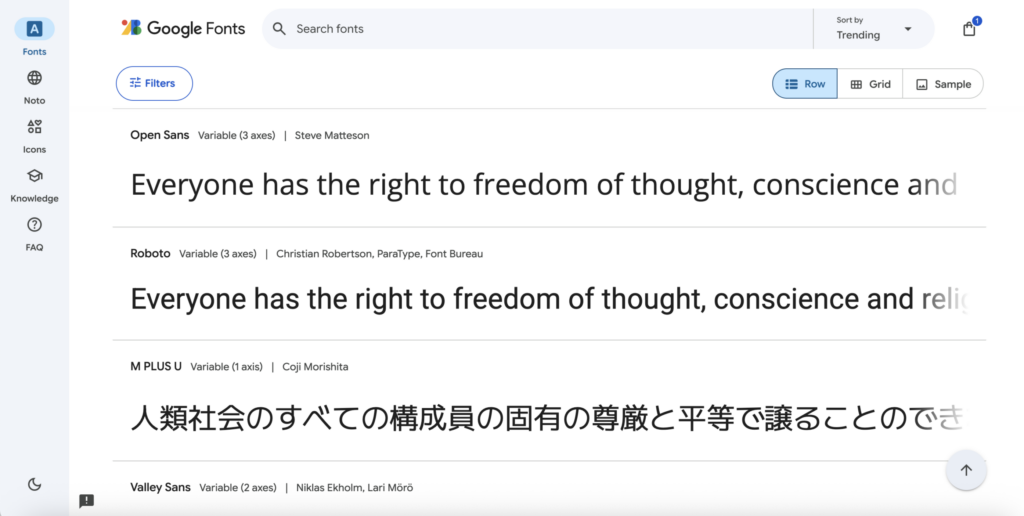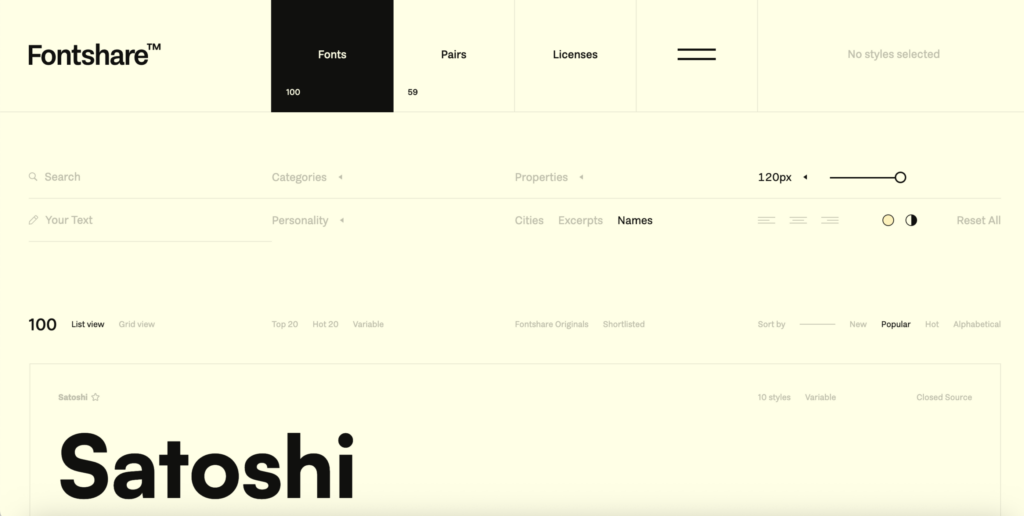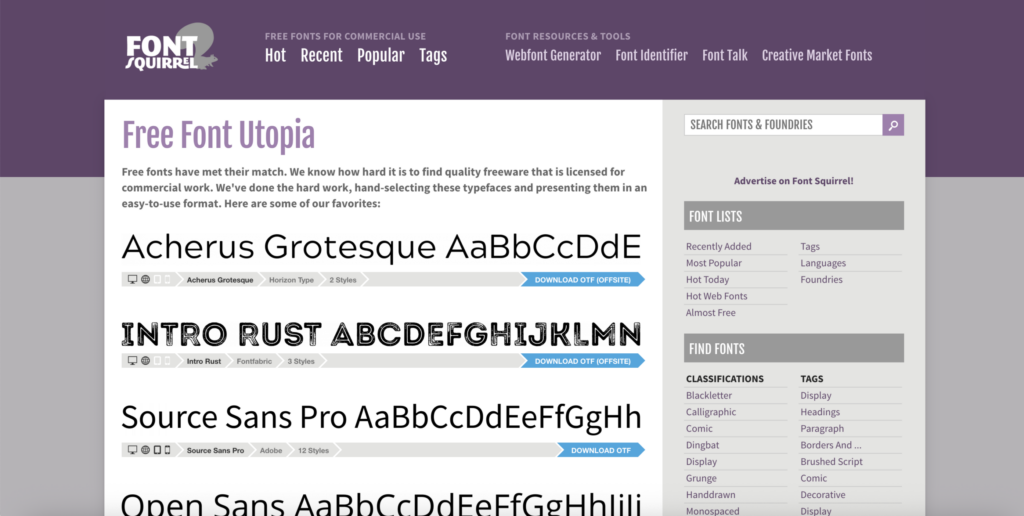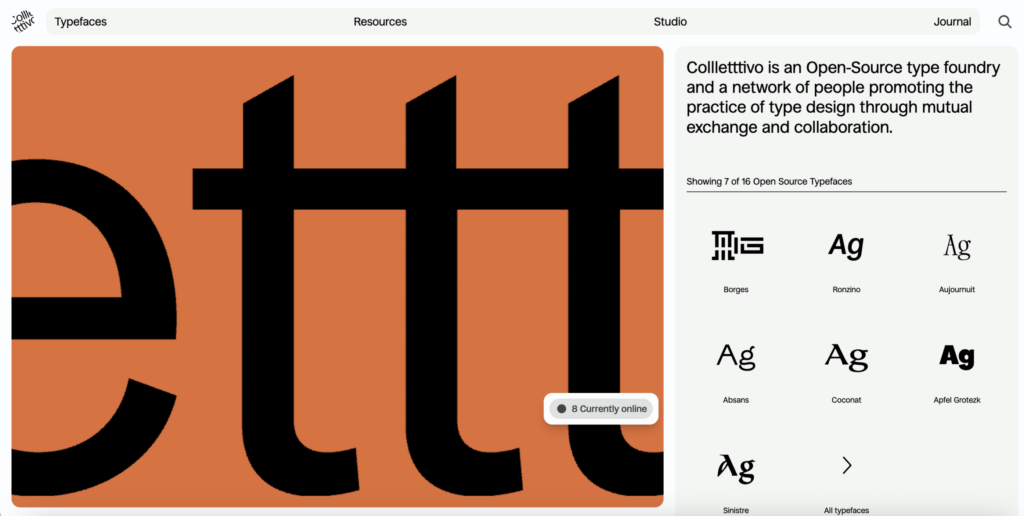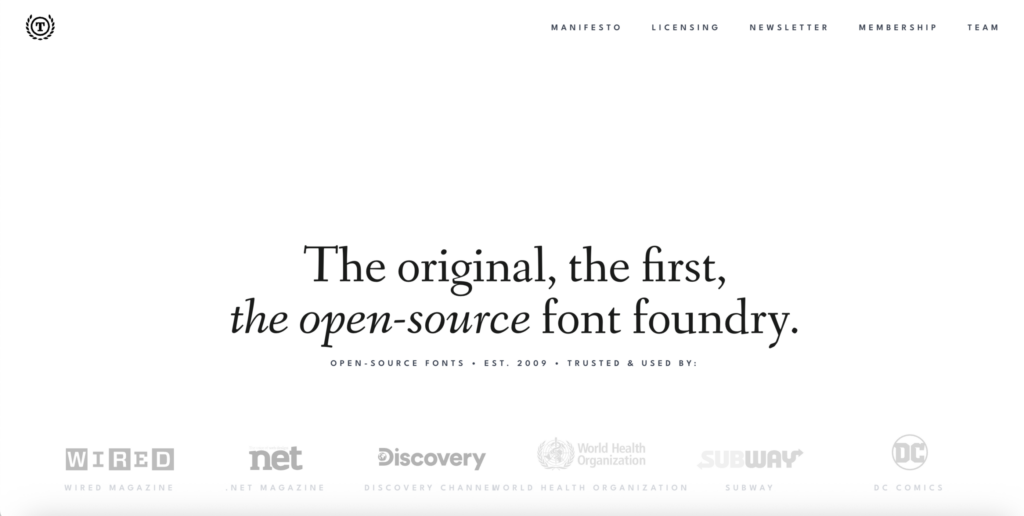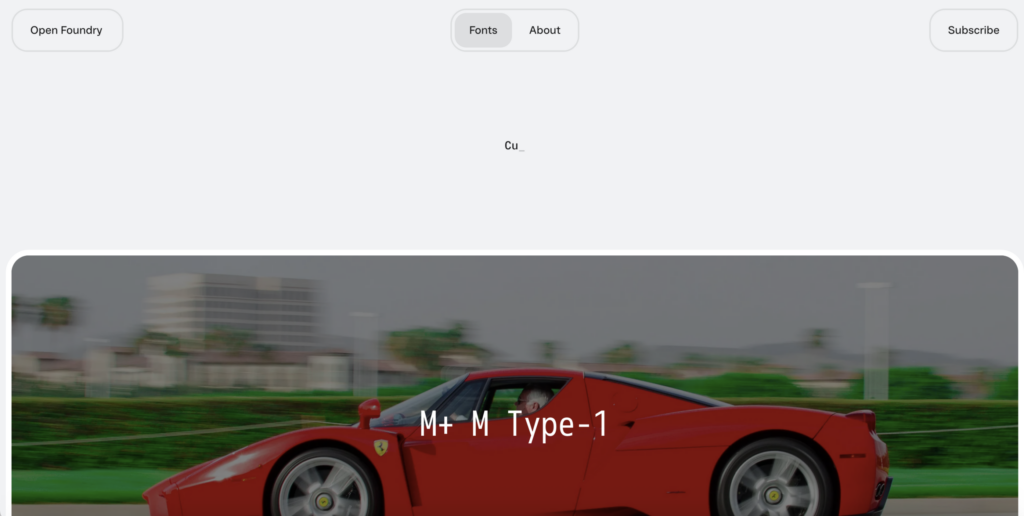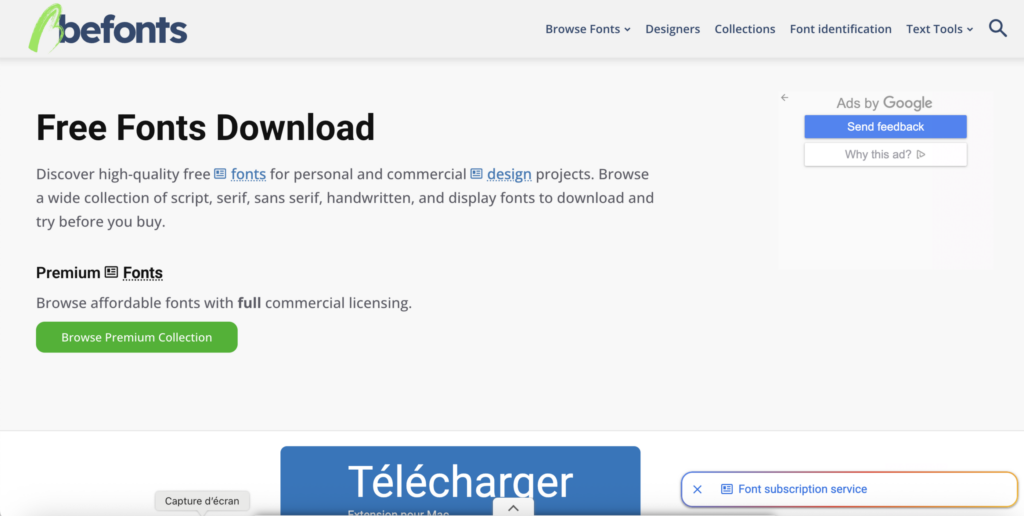
¿Dónde encontrar tipografías bonitas y gratuitas para proyectos comerciales?
Acabas de encontrar la tipografía perfecta. Encaja con tu logotipo, transmite exactamente el tono que buscabas y ya te imaginas utilizándola en todas partes.
Entonces abres la licencia: Solo para uso personal. Y vuelta a empezar…
Porque una tipografía gratuita no es necesariamente gratuita para proyectos comerciales. Utilizar una fuente en el logotipo de un cliente, en un packaging, un cartel, una campaña publicitaria o cualquier soporte destinado a una empresa puede requerir una licencia específica.
Por suerte, hoy en día existen muy buenas plataformas para encontrar tipografías gratuitas, de calidad y utilizables en proyectos profesionales.
Aquí te proponemos unas muy interesantes.
Tipografías gratuitas: ¿se pueden usar en proyectos comerciales?
Antes de descargar una tipografía, hay que tener en cuenta lo siguiente:
Una tipografía puede ser:
• gratuita únicamente para uso personal;
• gratuita para determinados usos comerciales;
• totalmente libre para proyectos personales y comerciales;
• ofrecida bajo una licencia de código abierto;
• disponible gratuitamente en versión de prueba, pero de pago para su uso final.
Y la diferencia es importante.
Crear una invitación de cumpleaños con una tipografía gratuita no tiene las mismas implicaciones que utilizarla en la identidad visual de una empresa o en 10.000 envases.
Por eso, antes de utilizar una tipografía en un proyecto profesional, comprueba siempre la licencia asociada a ella.
1. Google Fonts: una apuesta segura para proyectos comerciales
Google Fonts es probablemente la plataforma más sencilla para encontrar tipografías gratuitas para utilizar en proyectos profesionales.
Las tipografías disponibles se distribuyen bajo licencias de Open Source (código abierto) y pueden utilizarse tanto en proyectos personales como comerciales. Google indica expresamente que pueden utilizarse en proyectos comerciales.
La biblioteca es enorme y contiene todo tipo de tipografías:
• serif;
• sans serif;
• tipografías display;
• monoespaciadas;
• script;
• fuentes variables.
Entre ellas encontramos familias que se han convertido en imprescindibles, como Inter, Poppins, Manrope, DM Sans, Playfair Display o Space Grotesk.
Ideal para: branding, sitios web, publicaciones, carteles y proyectos para clientes.
Lo mejor: las licencias son mucho más fáciles de entender que en las plataformas que combinan distintos tipos de derechos.
2. Fontshare: para encontrar tipografías gratuitas con un acabado realmente premium
Fontshare es probablemente una de las mejores alternativas a Google Fonts cuando buscas algo con más personalidad.
La plataforma fue creada por Indian Type Foundry y ofrece una selección de tipografías de calidad profesional.
Lo más importante es que Fontshare especifica que todas las tipografías de su catálogo son gratuitas para uso personal y comercial. Según la familia tipográfica, se ofrecen bajo una licencia de código abierto o bajo una licencia gratuita propia de Indian Type Foundry.
La diferencia con algunas de las grandes bibliotecas de tiografias gratuitas se aprecia enseguida: la selección se acerca mucho más a lo que esperaríamos de una fundición tipográfica premium.
En ella encontrarás tipografías especialmente adecuadas para:
• identidades visuales;
• titulares editoriales;
• campañas publicitarias;
• sitios web;
• presentaciones de marca.
Ideal para: identidades modernas y proyectos que quieran evitar el efecto de «Google Fonts de siempre».
Lo mejor: una selección de gran calidad y una licencia comercial clara.
3. Font Squirrel: el especialista en tipografías gratuitas para uso comercial
Font Squirrel se ha creado precisamente en torno a esta cuestión.
La plataforma selecciona principalmente tipografías que cuentan con una licencia que permite su uso comercial gratuito.
Aun así, es importante consultar la licencia específica de cada tipografía, ya que algunos usos concretos, como la integración en una aplicación o en un archivo digital, pueden estar sujetos a condiciones diferentes.
Visualmente, el sitio es algo menos actual que Fontshare, pero su catálogo sigue siendo muy interesante.
Además, puedes filtrar las tipografías por:
• serif;
• sans serif;
• script;
• display;
• retro;
• condensadas;
• monoespaciadas.
Ideal para: buscar una tipografía de uso libre para un proyecto de cliente sin tener que revisar cientos de licencias de «solo para uso personal».
Lo mejor: una plataforma especializada en tipografías que pueden utilizarse comercialmente.
4. Collletttivo: para encontrar tipografías mucho más creativas
Collletttivo es un estudio tipográfico independiente especialmente interesante si buscas tipografías menos convencionales.
Aquí nos alejamos claramente de las sans serif neutras que encontramos en todas partes.
El catálogo incluye tipografías muy gráficas y, en ocasiones, experimentales, como:
• Apfel Grotezk;
• Coconat;
• Mattone;
• Mazius Display;
• Ortica;
• Sprat.
Todas las tipografías de Collletttivo se publican bajo la SIL Open Font License. El estudio permite expresamente utilizarlas tanto en proyectos personales como comerciales, tanto en soportes impresos como digitales.
Ideal para: dirección de arte, carteles, identidades culturales, moda y branding creativo.
Lo mejor: tipografías mucho menos vistas que los grandes clásicos de la web.
5. The League of Moveable Type: los pioneros de la tipografía de código abierto
The League of Moveable Type es una referencia histórica de la tipografía de código abierto.
La plataforma apuesta por una selección reducida de familias en lugar de por un catálogo gigantesco.
Entre ellas encontramos:
• League Spartan;
• League Gothic;
• Raleway;
• Orbitron;
• Junction;
• Ostrich Sans.
Todas las tipografías que ofrece The League están bajo la Open Font License y pueden utilizarse en proyectos comerciales.
Es una buena opción si prefieres una selección reducida pero fiable en lugar de pasar una hora filtrando cientos de tipografías.
Ideal para: identidades visuales, publicaciones, web y carteles.
Lo mejor: una selección histórica y completamente de código abierto.
6. Open Foundry: para descubrir tipografías menos conocidas
Open Foundry funciona de una forma un poco diferente.
Es más bien una galería de tipografías de código abierto e independientes que una web clásica de descarga.
Las tipografías se seleccionan por su interés gráfico y, normalmente, Open Foundry redirige al sitio web del creador para descargarlas. Es una opción ideal para descubrir tipografías diferentes y salir de las de siempre.
Eso sí, hay que tener en cuenta que no todas las tipografías incluidas tienen exactamente la misma licencia. La propia Open Foundry recomienda consultar la licencia de cada familia antes de utilizarla en un proyecto para un cliente o con fines comerciales.
Ideal para: descubrir tipografías independientes y desarrollar una dirección de arte más original.
Lo mejor: una selección realmente orientada al diseño.
7. Befonts: muchas opciones, pero revisa bien la licencia
Befonts ofrece una enorme cantidad de tipografías gratuitas.
Y ese es, al mismo tiempo, su principal ventaja… y su principal riesgo.
A diferencia de Fontshare o Google Fonts, no todas las tipografías de la plataforma son necesariamente gratuitas para uso comercial.
Algunas son:
• gratuitas para uso personal;
• disponibles en versión de demostración;
• gratuitas para uso comercial;
• están sujetas a una licencia específica.
Por suerte, Befonts cuenta con una categoría específica de tipografías gratuitas para uso comercial.
La propia web también recuerda que la licencia de cada tipografía es la referencia que hay que consultar antes de utilizarla.
Ideal para: buscar tipografías más decorativas, retro o display.
Lo mejor: una variedad enorme.
Atención: no descargues una tipografía simplemente porque aparezca como «free font». Comprueba siempre su licencia y asegúrate de que permite el uso comercial.
¿Cómo saber si una tipografía es realmente gratuita para un trabajo para un cliente?
Lo más sencillo es buscar términos como:
«Commercial use allowed « o «Free for personal and commercial use» También puedes encontrar la mención: SIL Open Font License — OFL
Se trata de una licencia de código abierto muy habitual en el mundo de la tipografía que permite, entre otras cosas, utilizar la tipografía en trabajos comerciales, siempre que se respeten sus condiciones.
En cambio, si ves: «Personal use only» la tipografía normalmente no puede utilizarse de forma gratuita para una empresa, un cliente o un trabajo comercial.
¿Un logo, un cartel o un packaging se consideran uso comercial?
En la mayoría de los casos, sí.
Si trabajas para una empresa, una marca o un cliente, considera que estás en un contexto comercial.
Esto incluye, entre otros:
• un logo;
• una identidad visual;
• una tarjeta de visita;
• un packaging;
• un cartel publicitario;
• un folleto;
• un rótulo;
• un sitio web profesional;
• contenido para redes sociales de una marca;
• productos destinados a la venta.
Ten en cuenta también que no es lo mismo utilizar una tipografía en un diseño que compartir el archivo de la tipografía con otra persona.
Una licencia puede permitirte perfectamente imprimir un cartel con una determinada tipografía y, al mismo tiempo, prohibir que envíes directamente el archivo de la tipografía a otra persona.
Nuestro consejo: guarda siempre la licencia junto con la tipografía
Hoy estás trabajando en un proyecto de branding.
Tres años después, el cliente te pregunta si puede utilizar esa tipografía en su nuevo packaging.
Y ya no recuerdas en absoluto de dónde la sacaste.
Para evitar esta situación, acostúmbrate a guardar en la carpeta del proyecto:
• el archivo de la tipografía;
• el archivo de licencia;
• el nombre del creador o del estudio tipográfico;
• el enlace a la página de descarga.
Unos segundos hoy pueden ahorrarte una auténtica búsqueda del tesoro unos años más tarde.
¿Cómo elegir una buena tipografía para impresión?
Una tipografía puede verse espectacular en Behance y resultar mucho menos convincente cuando se imprime a 8 puntos en un catálogo.
Antes de elegirla, pruébala siempre en las condiciones reales en las que vas a utilizarla.
Comprueba su legibilidad en tamaños pequeños
Las tipografías muy finas o con mucho contraste pueden perder legibilidad cuando se imprimen en tamaños pequeños.
Prueba siempre los textos corrientes al tamaño final al que se van a imprimir.
Comprueba qué diferentes grosores tiene disponibles
Una familia que incluya varios grosores suele ser mucho más fácil de utilizar en una identidad visual completa.
Por ejemplo:
Regular
Medium
Semibold
Bold
te permitirán crear desde el principio una jerarquía tipográfica clara.
Comprueba los caracteres disponibles
Es un error bastante habitual.
Tu magnífica tipografía gratuita puede tener las letras de la A a la Z… pero quizá no incluya:
• las letras acentuadas;
• algunos símbolos;
• el signo €;
• las ligaduras;
• las cifras que necesitas para tu proyecto.
Antes de utilizarla en una identidad visual, escribe algunas frases que contengan:
À Á Ñ Ç o € 0123456789
Así podrás comprobar rápidamente si la familia está lo suficientemente completa.
Pruébala sobre papel
Por último, si la tipografía tiene un papel importante en tu identidad visual, imprímela.
Una tipografía muy fina en pantalla puede resultar demasiado delicada sobre papel, mientras que otra que parece ligeramente gruesa en pantalla puede quedar perfectamente equilibrada una vez impresa.
Los 3 sitios que deberías abrir primero
Si no quieres recorrer siete plataformas para cada proyecto, empieza por:
Google Fonts, por la cantidad y la sencillez.
Fontshare, para encontrar familias con un acabado más premium.
Collletttivo, cuando buscas algo más creativo y menos convencional.
Después, puedes recurrir a Font Squirrel, Open Foundry o Befonts cuando necesites ampliar la búsqueda.
Una buena tipografía también necesita una licencia adecuada
Elegir una tipografía no debería reducirse a: «es bonita, así que la descargo»».
Para un proyecto profesional, una buena tipografía debe cumplir varios requisitos:
• adaptarse al universo gráfico;
• mantener una buena legibilidad;
• incluir los caracteres necesarios;
• funcionar correctamente en los distintos soportes;
• contar con una licencia adecuada.
Y, sobre todo, recuerda que una tipografía que aparece como gratuita en internet no es automáticamente gratuita para uso profesional.
Por eso, el mejor hábito es muy sencillo: encuentra la tipografía, comprueba su licencia y solo después empieza a utilizarla.